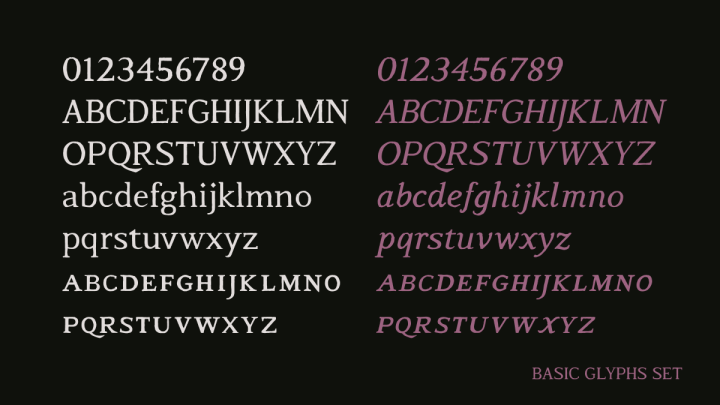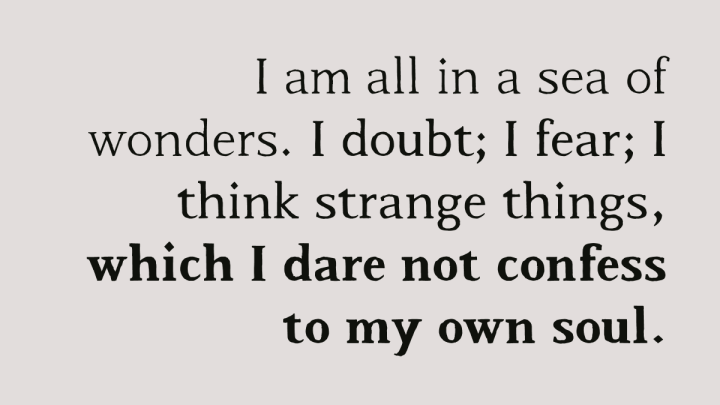
免费beholden book字体素材,是Beholden字体的迭代版本 ,Beholden 字体是一种手绘衬线字体。 最初的 Beholden 字体是由字形图转换而来,仅做了极少的修改。此次修订版对字体进行了进一步的优化,平衡了字距差异并统一了基线,旨在使其成为更适合长篇正文的字体。 该字体包含三种字重(细体、常规体和粗体)及其斜体。 声明:本站所有文章,均来源于网络用户收集上传。如若本站内容侵犯了原著者的合法权益,可联系我们进行处理。